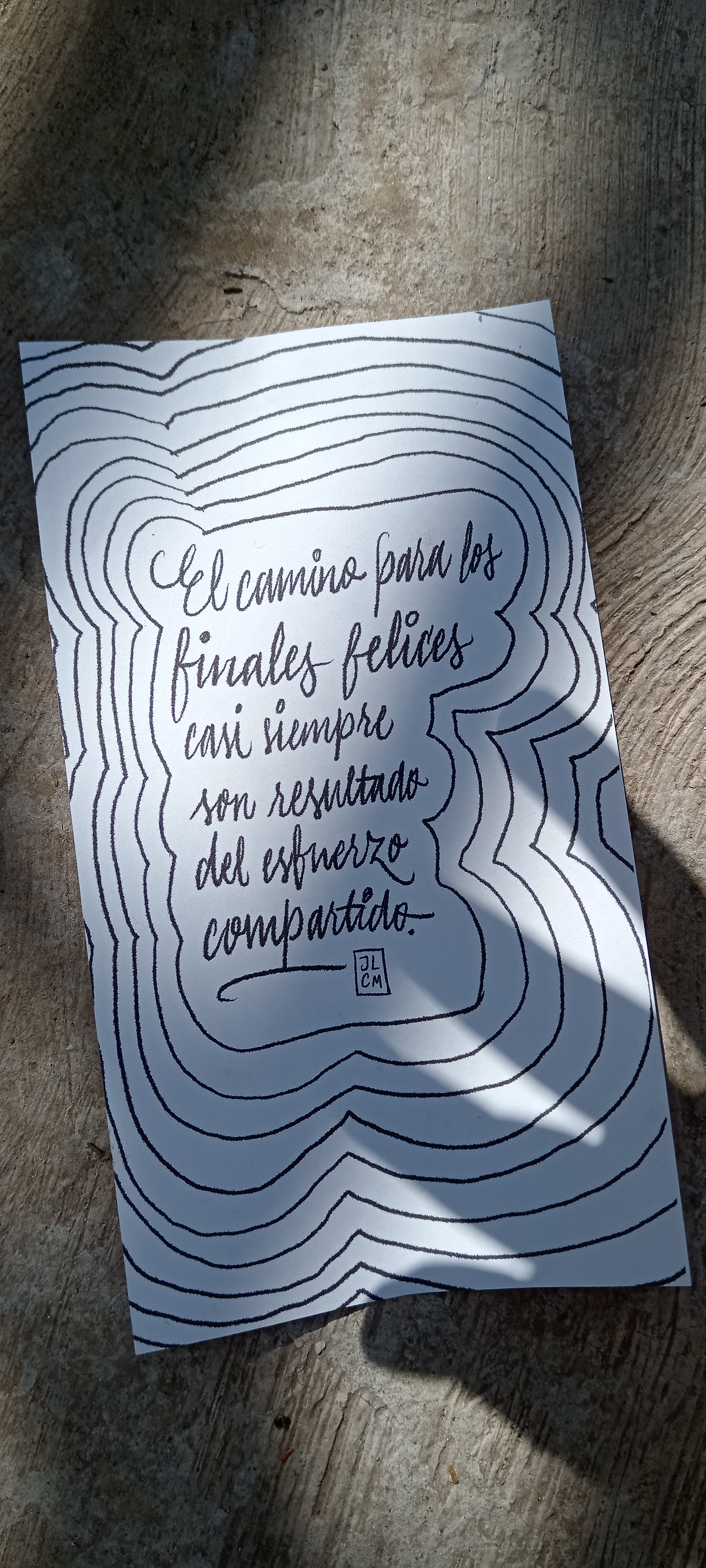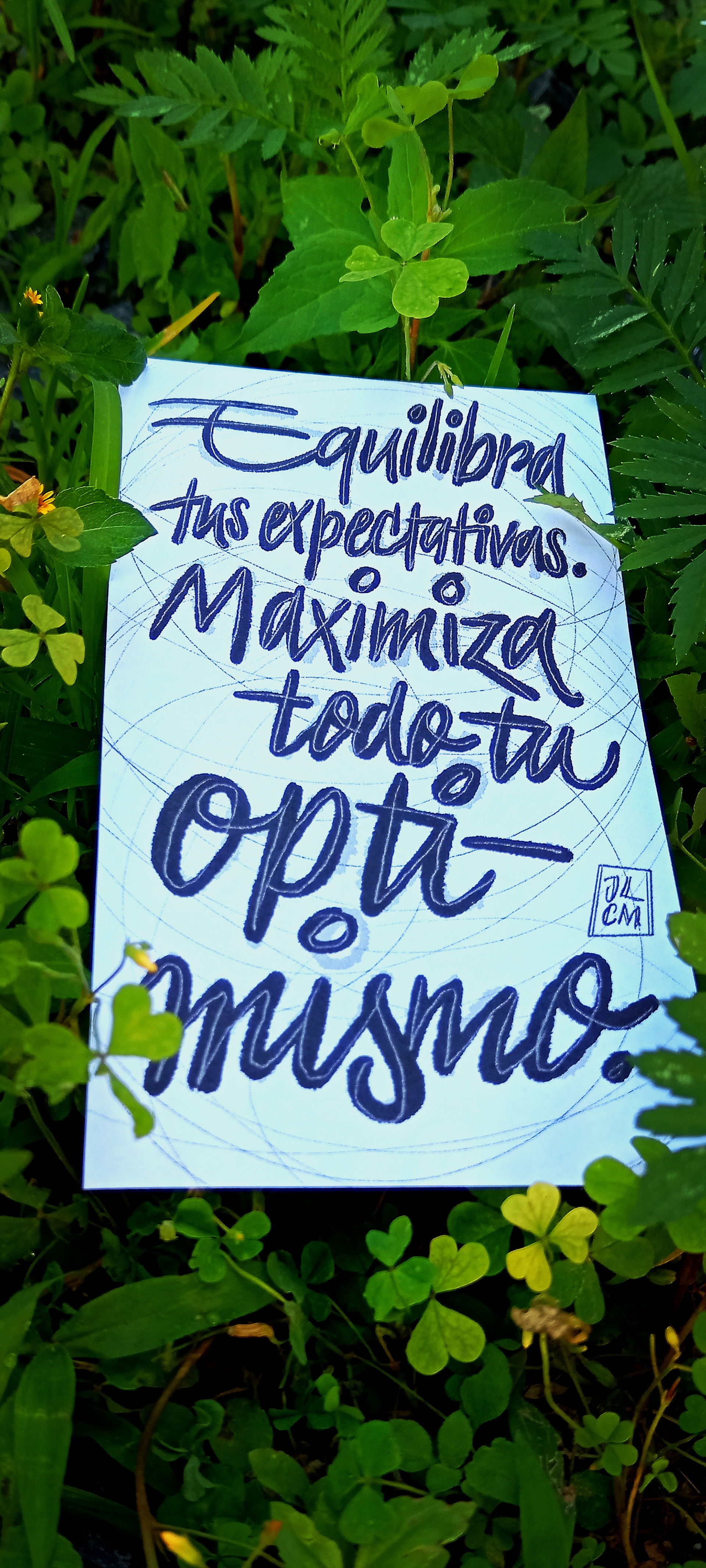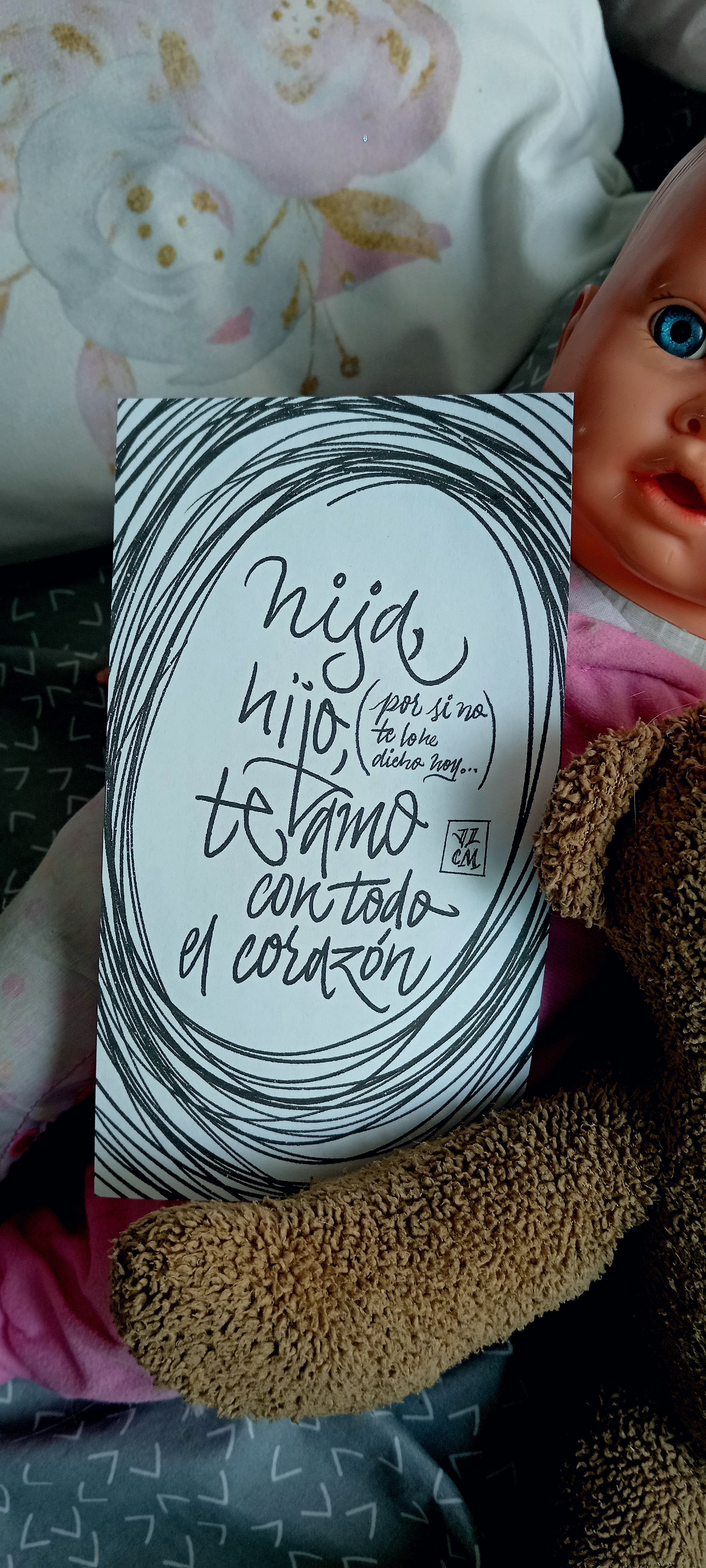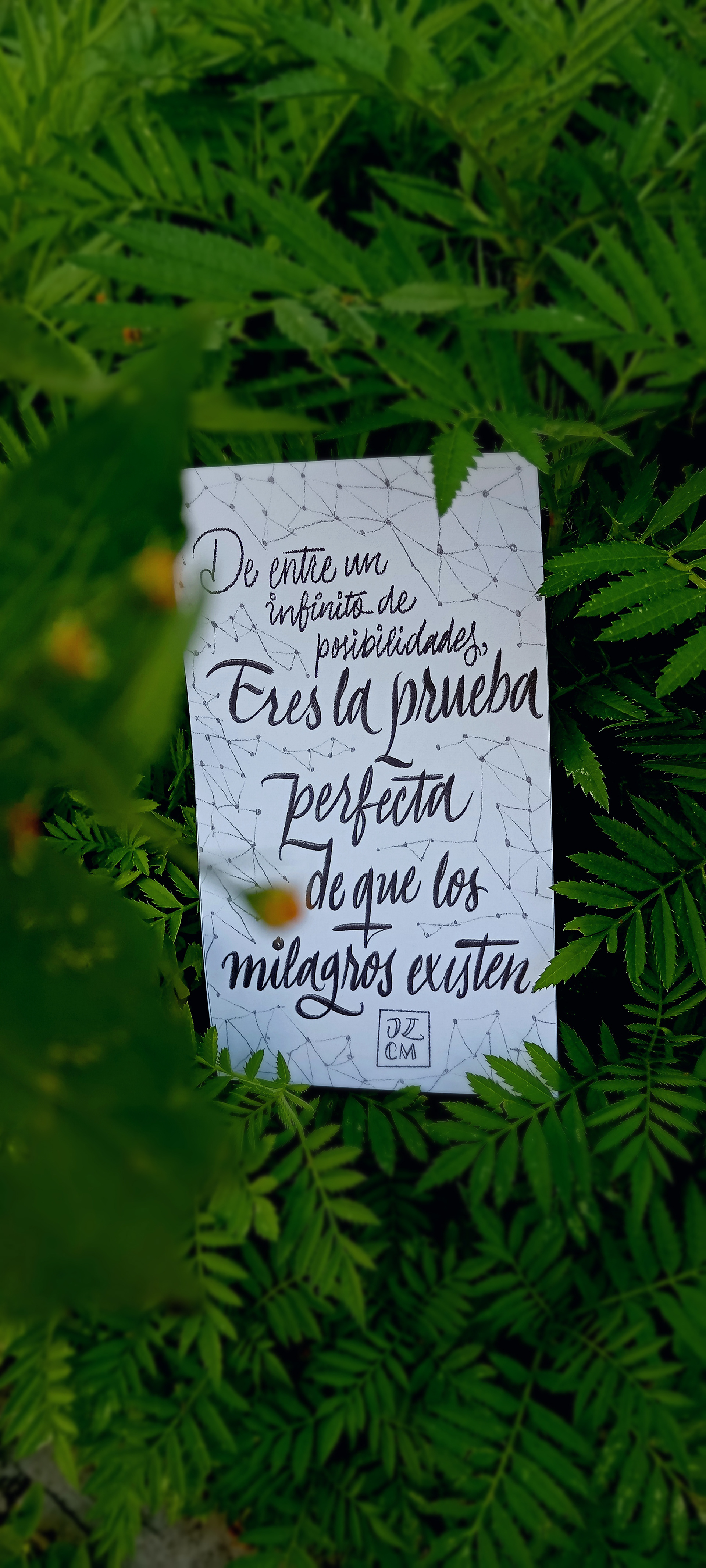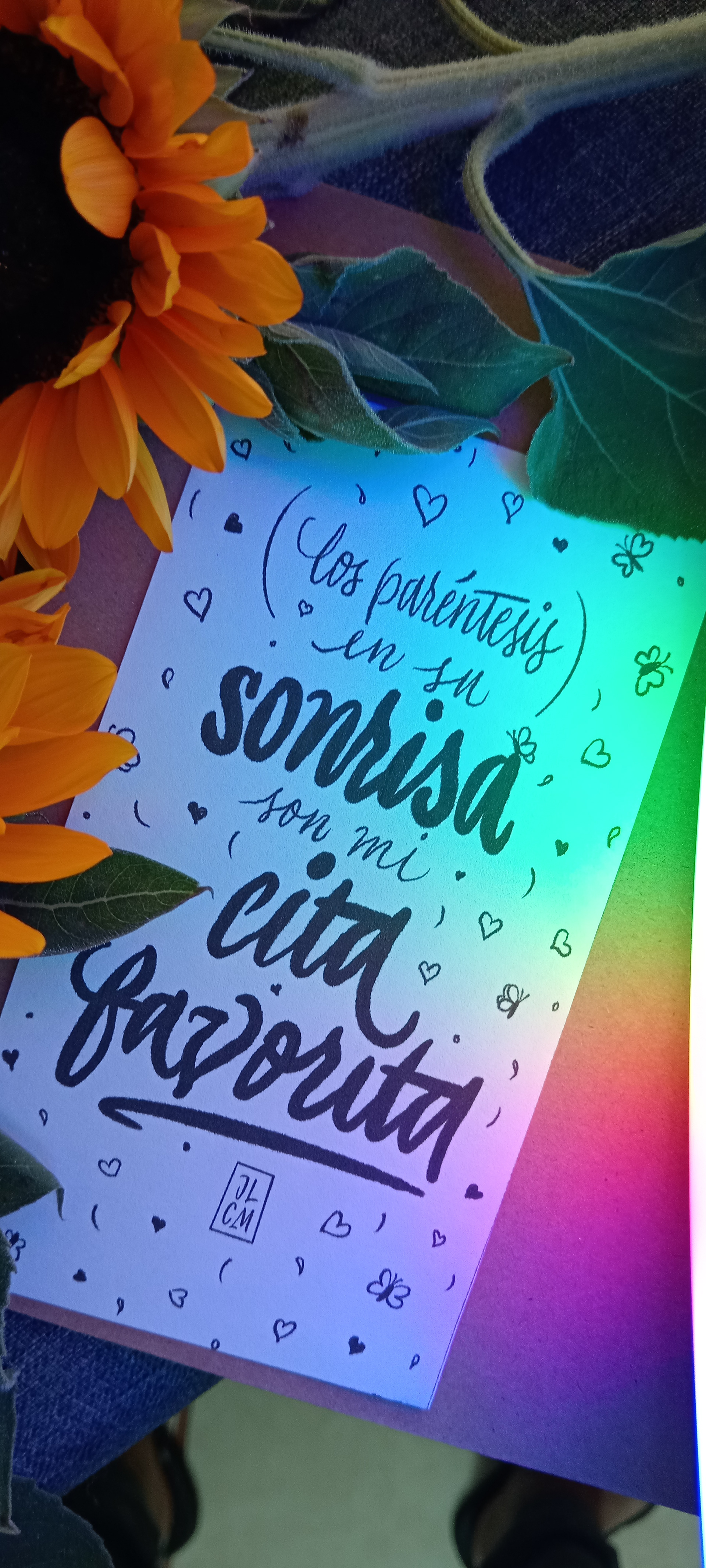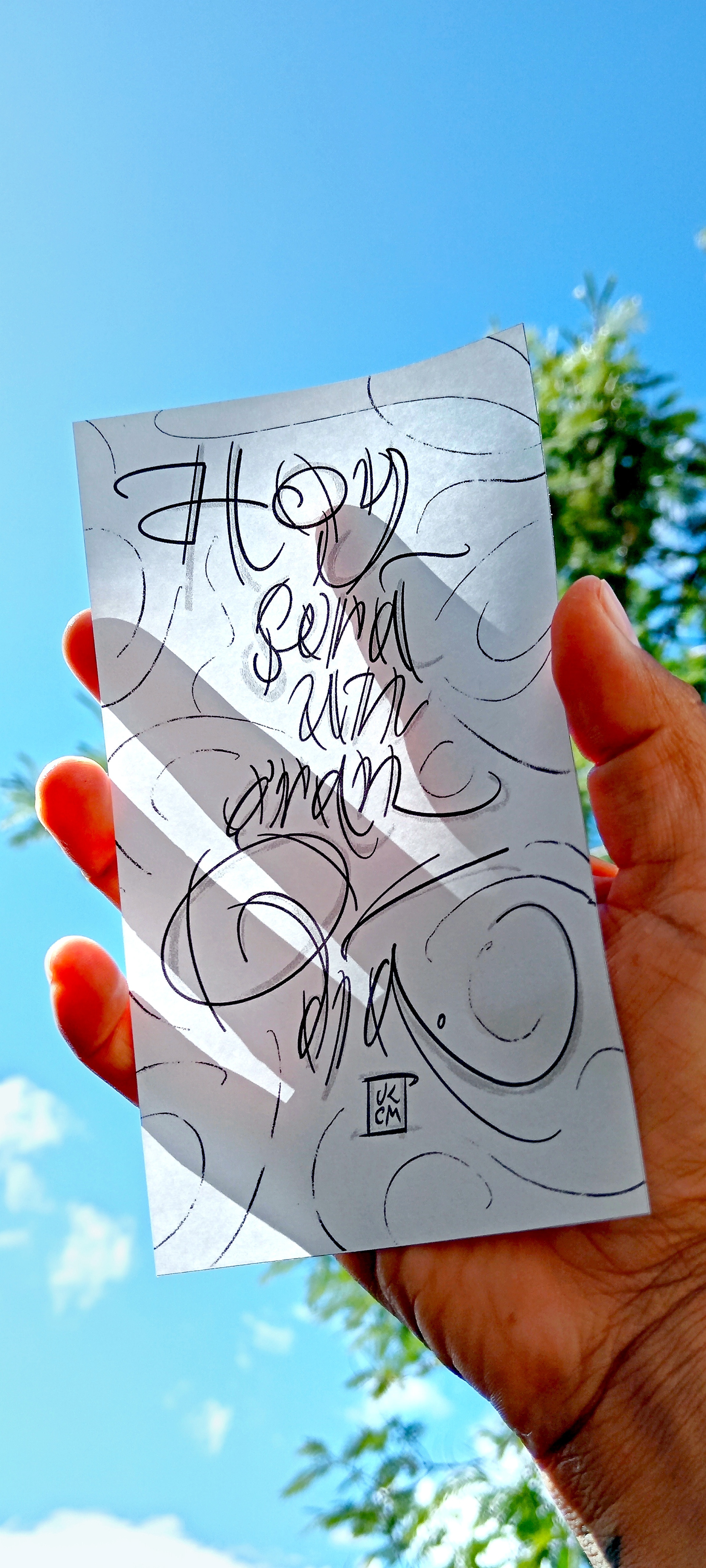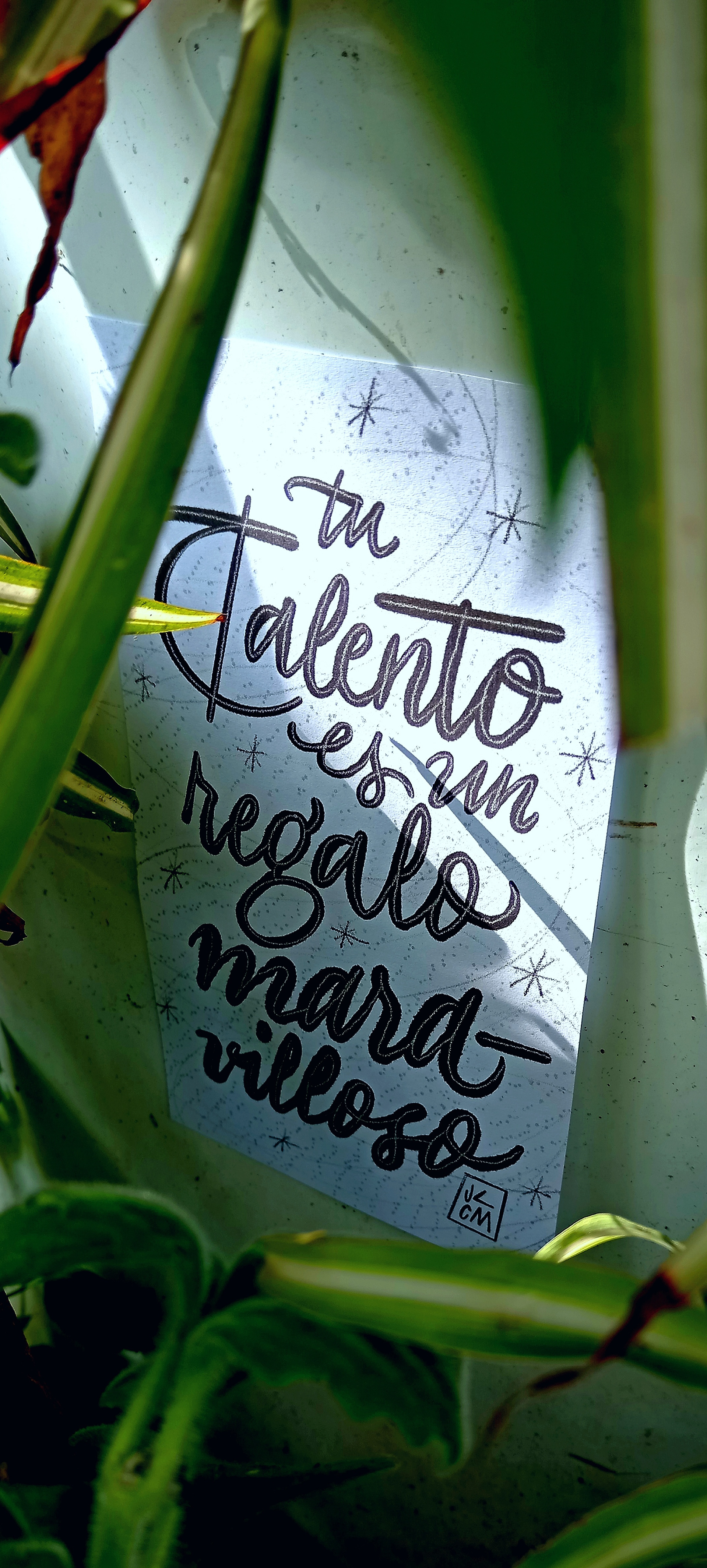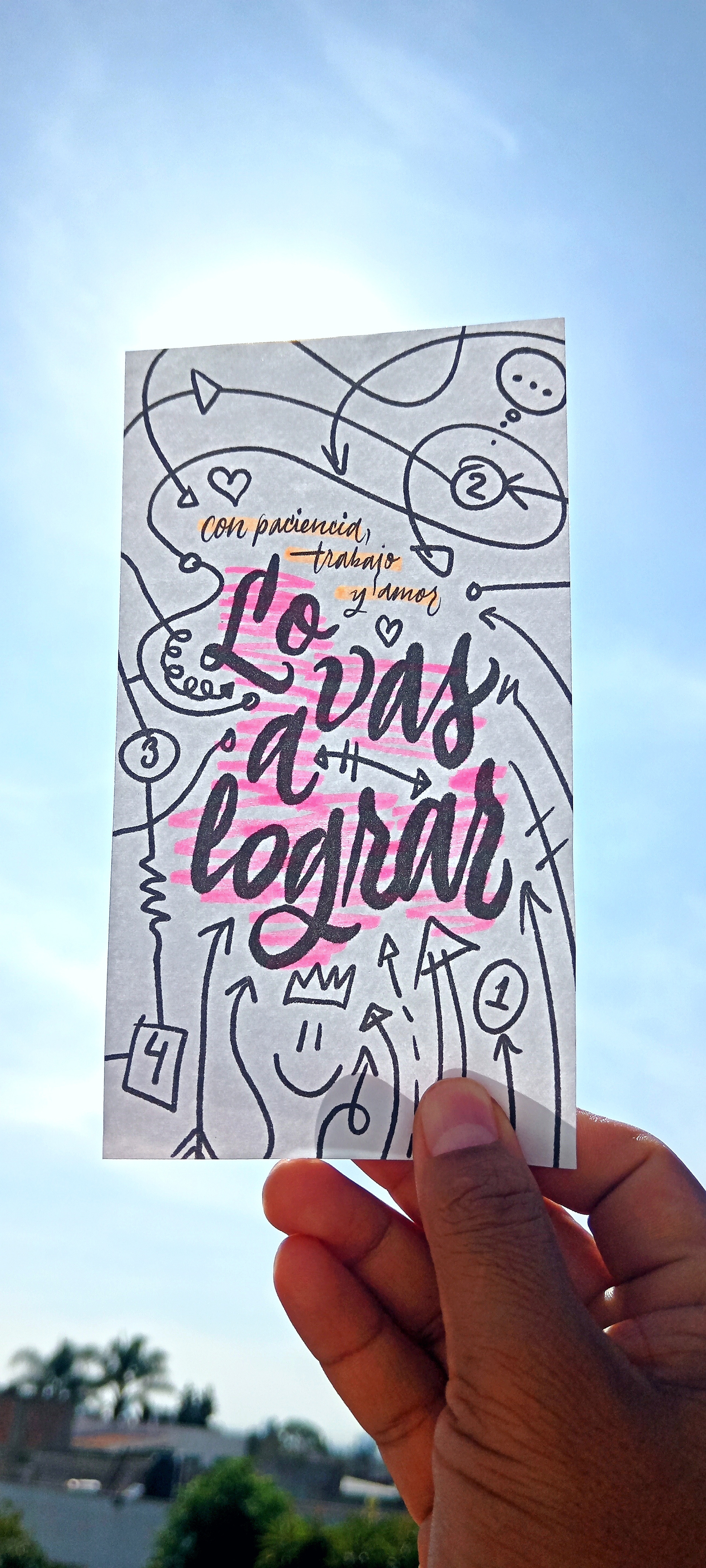
EL SOL CAMINA CONMIGO 02
Segunda edición de mi proyecto personal y continuación de "El Sol Camina Conmigo": una serie de postales digitales e historias para redes sociales con mensajes positivos sobre la vida, el amor, el amor propio, el cariño y la buena voluntad, escritos especialmente para esta ocasión. En esta segunda temporada, me propuse cumplir ciertas tareas, como crear la composición tipográfica en Procreate (iPad), todo en blanco y negro, con diferentes estilos caligráficos desgastados e incluso ilustraciones y fondos.
Cada postal se creó en formato digital, pero también se imprimieron y se colocaron en un pequeño escenario para fotografiarlas y que combinaran con el texto, ampliando así su significado. Este ejercicio se convirtió en una forma fantástica de explorar diferentes estilos para expresar sentimientos y pensamientos sobre mi vida.
Ésta colección cuenta con 36 piezas creadas entre junio, julio y agosto de 2024 para redes sociales, principalmente Instagram y Facebook.